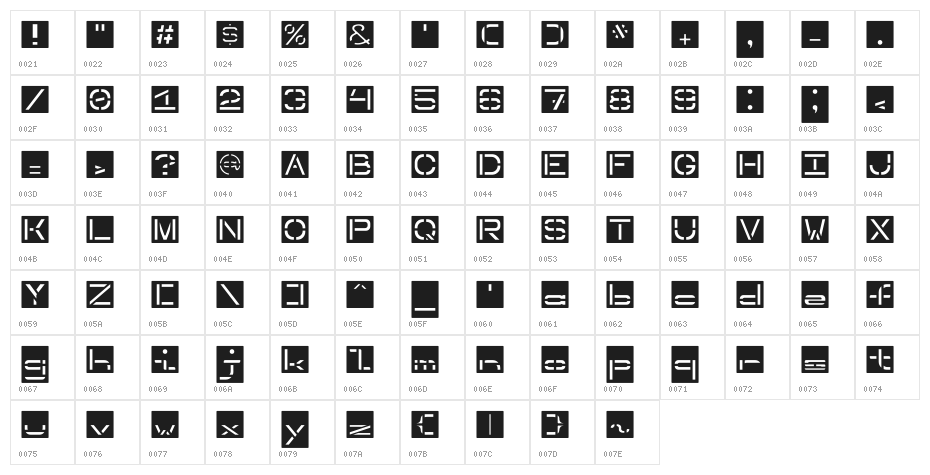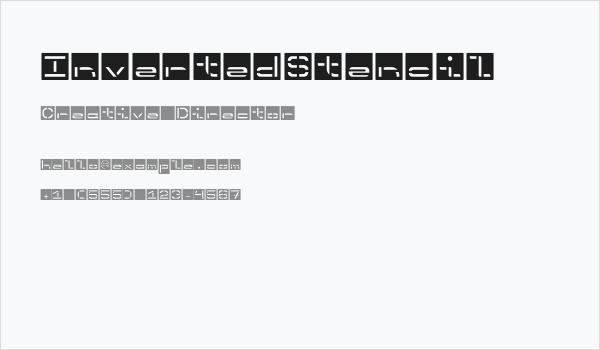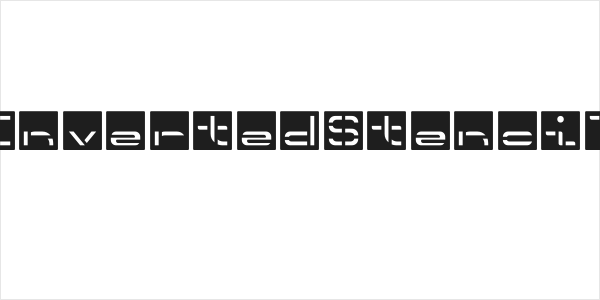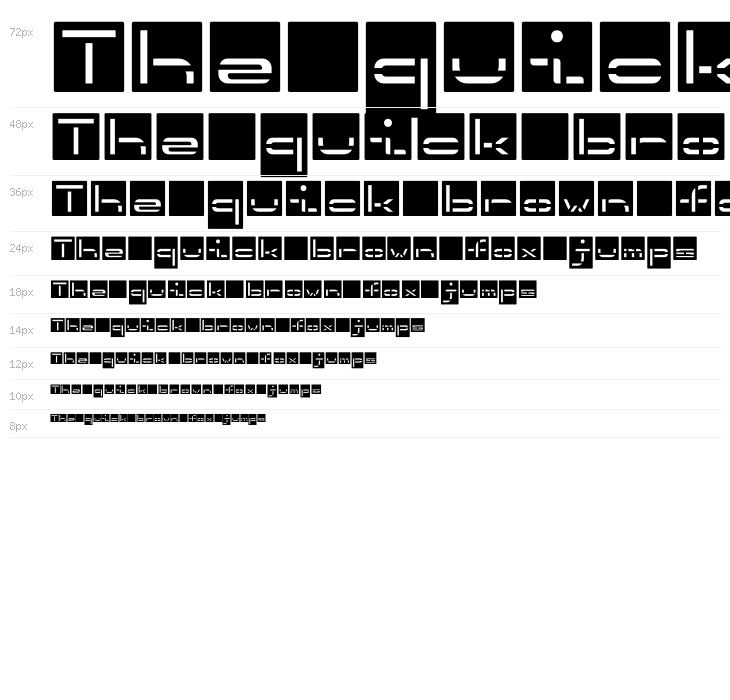
InvertedStencil Font
| Categorie | Stencil |
| Spaziatura caratteri | Normal |
| Stile generale | Modern, Industrial |
| Progetti proposti | Ideal for posters, industrial-themed designs, branding, and signage that require a bold and impactful statement. |